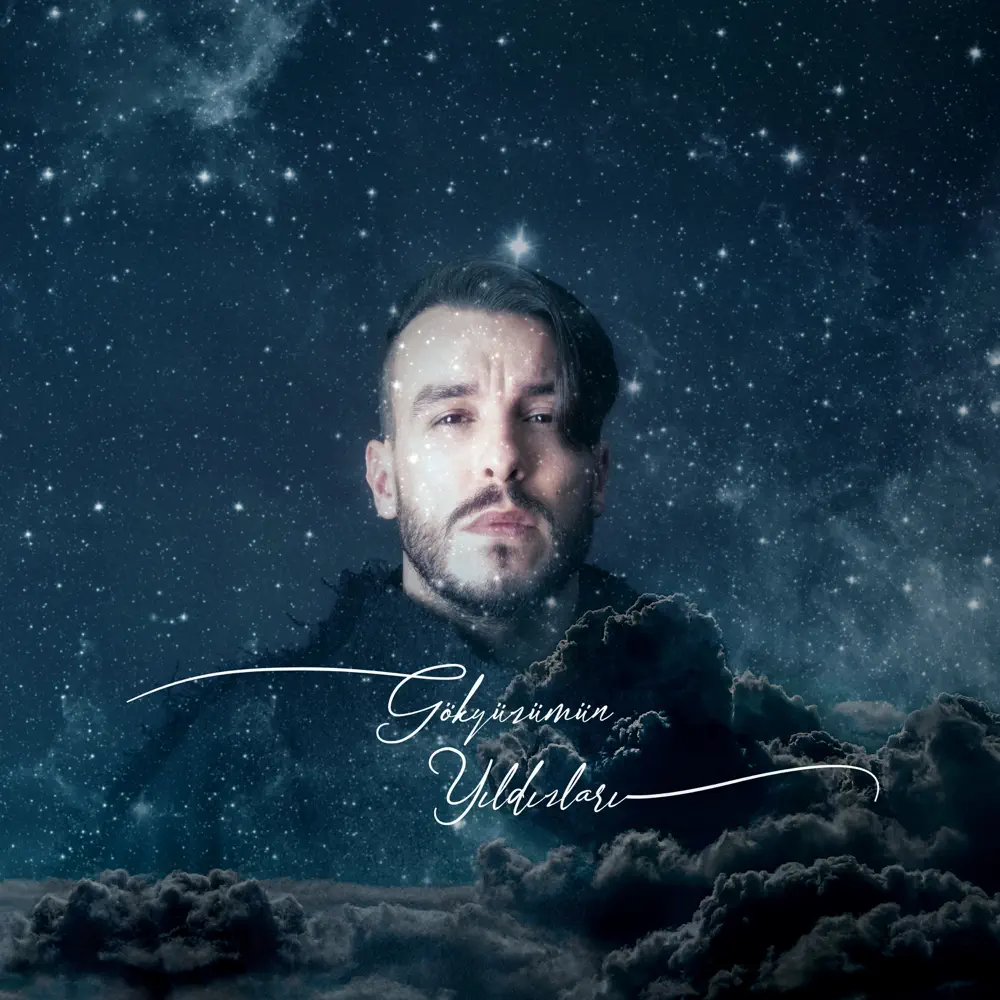
Az önce dikkatli bakara fark ettiğim yazının fontu çok hoşuma gitti. Kullanmak istiyorum ama font bulma sitelerinde yeterince verimli bir sonuç elde edemedim.
Açıkçası kendi el yazısı olabileceği düşüncesindeyim fakat bu konuda tecrübeli arkadaşlar yardımcı olabilir mi?